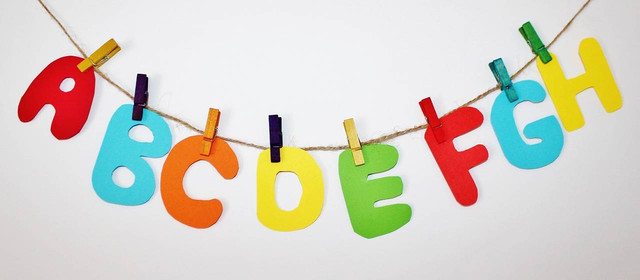
10 Jenis Font Pilihan untuk Desain dan Menulis Buku
Dalam proses membuat tulisan atau desain perlu pengetahuan untuk mengenal dan mempelajari berbagai jenis font. Mengenal dan mempelajari macam-macam jenis font sangatlah penting.
Hal ini disebabkan setiap jenis font memiliki bentuk dan karakter yang berbeda-beda. Berikut ini adalah beberapa jenis font yang mungkin dapat menjadi pilihan dalam desain hingga penulisan.
Jenis Font Pilihan dalam Menulis dan Desain Grafis
Dikutip dari Buku “Corel Draw Untuk Bisnis" yang ditulis oleh Hasto Prayoga terbitan Elex Media Komputindo, terdapat beberapa jenis font dan karakternya yang dapat menjadi pilihan dalam desain dan menulis.
1. Serif
Jenis font ini sering digunakan karena bentuknya lebih mudah dibaca.
2. San-Serif
Font San-Serif adalah versi kebalikan dari font serif. Bentuk font San-Serif tidak memiliki lengkung di setiap sudut hurufnya sehingga bersifat tegas dan jelas karakternya.
3. Slab Serif
Font slab serif memiliki ciri kotak dan tegas, rapat antara satu huruf dengan huruf yang lain.
4. Script
Font Script memiliki bentuk yang mirip dengan tulisan tangan dengan garisan halus dan cenderung miring.
5. Comic
Memiliki ciri bentuk tulisan yang friendly dan enak dibaca, sering digunakan untuk desain dan pengetikan buku-buku komik.
6. Blackletter
Font ini menampilkan gaya goresan yang melengkung dan rumit, seperti tulisan tangan di zaman Victoria.
7. Stencil
Font stencil lebih sering digunakan untuk untuk publikasi di surat kabar, misalnya pada bagian hideline suatu berita.
8. Dekoratif
Font dekoratif itu sendiri merupakan huruf yang dikembangkan dari huruf-huruf yang sudah ada, biasanya digunakan sebagai ornamen atau hiasan pada bagian penting suatu teks.
9. Commercial
Font Commercial adalah bentuk font yang paling umum digunakan untuk kepentingan setting, desain, dan percetakan.
10. Expert Font
Expert font khusus dikemas untuk kepentingan kerja profesional. Expert font memungkinkan penggunanya untuk bereksplorasi lebih dengan adanya ligature, swash, dan alternatif font.
Masih banyak jenis font dengan karakter berbeda yang dapat ditemukan sebagai pilihan dalam menulis maupun desain grafis. Oleh karena itu menjadi pertimbangan yang penting dalam penggunaannya bagi seorang desain grafis untuk memilih dengan tepat jenis font manakah yang sesuai dengan desain yang diinginkan. (SR)